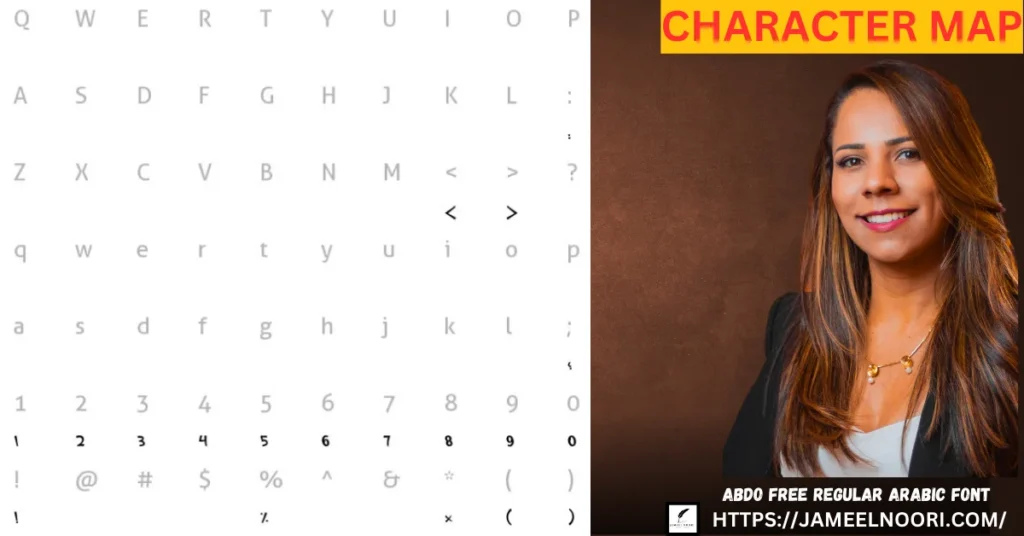
Abdo Free Regular Arabic Font aik modern aur stylish TrueType font hai jo designers aur content creators ke liye bohat popular hai. Yeh font 24452 martaba download ho chuka hai aur 436 users ne isay 4.44 out of 5 ki rating di hai. Is font ka unique calligraphy aur elegant design isay Urdu aur Arabic fonts ke shaukeen logon ke liye perfect banata hai.
Why Abdo Free Regular Arabic Font is the Best Choice for Designers
Abdo Free Regular Arabic Font designers aur typographers ke liye ek ultimate choice hai. Yeh font Urdu fonts aur Arabic fonts lovers ke liye specially optimized hai aur creative projects me professional look lata hai.
Key Features of Abdo Free Regular Arabic Font:
- Elegant Arabic calligraphy
- Easy to read and professional design
Why Abdo Free Regular Arabic Font is Perfect for Urdu and Arabic Projects
Abdo Free Regular Arabic TTF Font Urdu aur Arabic projects ke liye perfect hai kyunki:
- Yeh font professional aur readable hai
- Graphic design aur digital content me aesthetic look lata hai
Best Use Cases:
| Use Case | Description |
| Logo Design | Elegant calligraphy for brand identity |
| Social Media Posts | Attractive Urdu & Arabic typography |
| Print Design | Posters, flyers, and brochures |
| Digital Content | Blogs, websites, and digital campaigns |
Tips to Use Abdo Free Regular Arabic TTF Font Effectively
Abdo Free Regular Arabic Font ka proper use design aur readability dono me farq lata hai.
- Font size hamesha 12–18pt me rakhein
- Headlines ke liye bold aur body text ke liye regular style use karein
- Color contrast strong rakhein taki font readable ho
Pro Tips:
- Multiple fonts combine karte waqt Abdo Free Regular ko primary font rakhein
- Urdu fonts aur Arabic fonts ke sath seamlessly integrate karein
Abdo Free Regular Arabic Font aik best choice hai designers aur content creators ke liye, jo Urdu aur Arabic projects me professional aur stylish look chahte hain. Is font ka modern calligraphy, easy installation aur free availability isay Pakistan me sab designers ke liye ideal banata hai.
Agar aap Urdu fonts aur Arabic fonts ki search me hain, to Abdo Free Regular Arabic Font aap ke liye ultimate solution hai.
Is this font suitable for Urdu writing?
Yes, it is perfect for Urdu typography and Arabic scripts.
Can I use it for logo designs?
Yes, the elegant calligraphy makes it ideal for logos and branding.